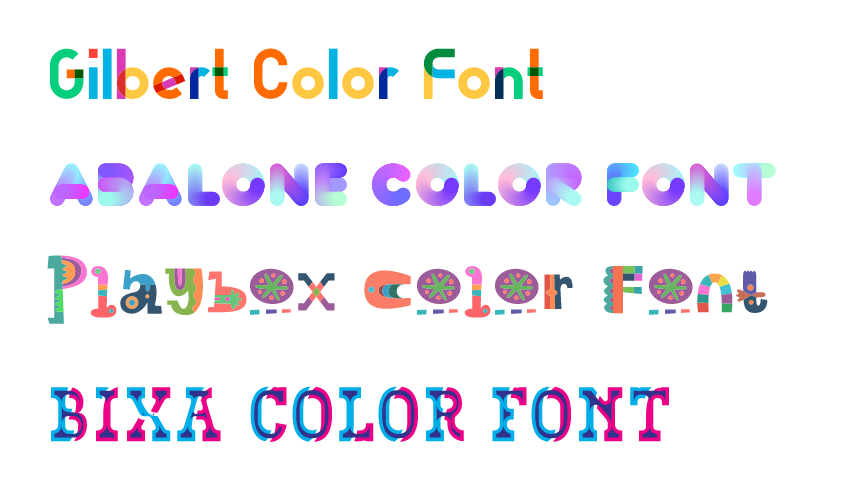
مطمئنا تمام طراحان وب می‌دانند که چگونه یک رنگ را روی فونت‌ها اعمال کنند. وقتی که شروع به یادگیری CSS می‌کنید این موضوع از ساده‌ترین چیزهایی است که با آن برخورد می‌کنید. یک رنگ را انتخاب کرده و بعد با استفاده از خاصیت color آن را اعمال می‌کنید: color:blue;. وقتی این کار را انجام می‌دهید تنها یک رنگ وجود دارد که اعمال می‌شود.
اما نظرتان چیست که بتوانیم چندین رنگ مختلف را به یک رشته یا یک متن اعمال کنیم؟ نظرتان چیست اگر بتوانیم متنی با رنگ آبی و بنفش داشته باشیم؟ یا آن را با استفاده از گرادینت اعمال کنیم؟ هدف اصلی این نوشته این است که بتوانیم چندین رنگ مختلف را به یک متن یا یک رشته اعمال کنیم.
تصویر زیر گویای چیزی که می‌خواهیم ایجاد کنیم است:
شاید فکر کنید این تصویر در یک محیط گرافیکی با استفاده از ابزاری مانند فوتوشاپ و… ساخته شده است، اما در حقیقت این کار توسط کدنویسی و از طریق مرورگر انجام شده است.
جدای از آنکه این رنگ‌ها از طریق CSS کنترل می‌شود، این فونت‌ها اطلاعات داخلی دارند که اجازه می‌دهند تا رنگ‌های مختلفی را در اختیار داشته‌ باشیم.
استفاده‌ از فونت‌های رنگی
فونت‌های رنگی تکنیک جدیدی در دنیای وب به حساب می‌آیند به همین دلیل است که تا به حال تعداد انگشت‌شماری از آن‌ها ارائه شده است. برخی از این فونت‌ها رایگان و برخی دیگر به صورت تجاری ارائه شده‌اند، من در این مطلب شما را با چند مورد رایگان آشنا می‌سازم. می‌توانید در لینک‌های زیر براساس نیازتان مواردی را دانلود کنید:
کدی که برای اضافه کردن آن‌ها به پروژه نیاز است، کد جدید یا عجیبی نیست، ما از همان دستور @font-face همیشگی استفاده می‌کنیم:
مرورگر و پشتیبانی
در حال حاضر از فونت‌های رنگی تنها در فایرفاکس و Edge به صورت کامل پشتیبانی می‌شود. کروم نیز در این بازه تقریبا قرار می‌گیرد اما آنقدر کامل نیست. مرورگر Opera نیز به صورت کلی از آن پشتیبانی نمی‌کند.
تغییرات CSS
در حال حاضر نمی‌توانیم از CSS برای تغییر رنگ‌هایی که در فونت‌های رنگی استفاده شده است، استفاده بکنیم. با این حال برای یک طراح فونت این کار که بتواند فونتی همراه با تفاوت‌های رنگی مختلفی ارائه دهد امکان پذیر است. این تفاوت‌ها را می‌توان از طریق خاصیت font-feature-settings مدیریت کنید.
می‌توانید در این پروژه چنین موضوعی را به صورت عملی مشاهده کنید.
رنگ‌ها ثابت هستند، حتی روی لینک‌ها
از آنجایی که رنگ‌ها در فونت اصلی ثابت هستند بنابراین خاصیت color در این حالت هیچگونه تاثیری نخواهد داشت، این موضوع شامل لینک‌ها و دیگر موارد نیز می‌شود. البته دیگر استایل‌ها مانند زیرخط‌دار کردن متون با فونت‌های رنگی هیچ مشکلی ندارد و می‌تواند به خوبی استفاده شود. از این طریق می‌توانید به کاربران‌تان دقیق‌تر بگویید که چه قسمتی از متن‌تان لینک است و چه قسمتی نیست.
یک مثال از این حالت را می‌توانید در زیر مشاهده کنید:
این کد به ما خروجی شبیه به زیر را خواهد داد:
در پایان
در بین فونت‌های رنگی و فونت‌های متغیر هر کدام می‌توانند ویژگی‌های جذاب و زیبایی را برای‌تان داشته باشد. این موارد می‌توانند روی دنیای تایپوگرافی طراحی وب در آینده تاثیر مثبت داشته باشند.